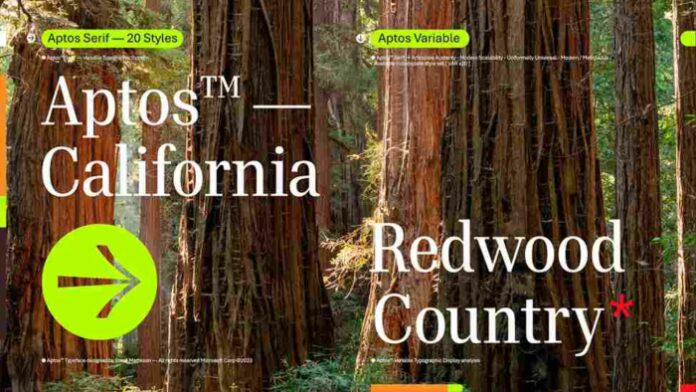
Telset.id, Jakarta – Kini para pengguna Microsoft Office akan mengalami perubahan besar secara tampilan, berkat font baru yang diberikan oleh perusahaan dari pembaruan terbarunya.
Setelah 15 tahun, Microsoft memutuskan mengganti font default di aplikasi 365 dan juga Office, font baru ini memiliki nama Aptos. Secara keseluruhan, ini akan terlihat seperti font sans-serif yang sederhana, namun perusahaan menjanjikan para pengguna akan menyukainya karena fleksibilitasnya.
Berdasarkan laporan dari Engadget, Aptos akan bisa digunakan dalam banyak bahasa. Selain itu, tersedia juga 4 font yang berbeda-beda, dan varian serif jika pengguna tidak ingin font yang terlalu modern.
Pembuat font ini Steve Matteson, yang juga membuat font pertama Windows, yaitu TrueType mengungkapkan bahwa Aptos terinspirasi dari kemanusiaan dan membangkitkan kepribadian seperti Carl Kassel dan Stephen Colbert.
Namun, hasil akhir dari font yang secara teoritis ini akan lebih mudah dibaca oleh setiap orang, dan juga eye-catching saat dipakai untuk menulis tugas esai dari sekolah hingga untuk presentasi perusahaan.
Font ini telah tersedia sebagai Bierstadt sebagai bagian dari upaya pengumpulan umpan balik, namun diluncurkan sebagai font default dari aplikasi Excel, Outlook, PowerPoint, dan Word untuk para penggunanya mulai hari ini.
Font lainnya akan tersedia dengan nama lamanya, seperti Grandview, Seafor, Skeena, dan Tenorite. Sementara itu, Aptos akan disematkan di bagian atas pemilih font, meskipun tidak wajib digunakan.
Meski begitu, font baru ini terlihat seperti ikon Office di tahun 2018 dan font ini juga tidak berdampak pada kemampuan mengetik para pengguna. Namun, ini bisa mnenjadi penyegaran bagi para pengguna aplikasi ini.